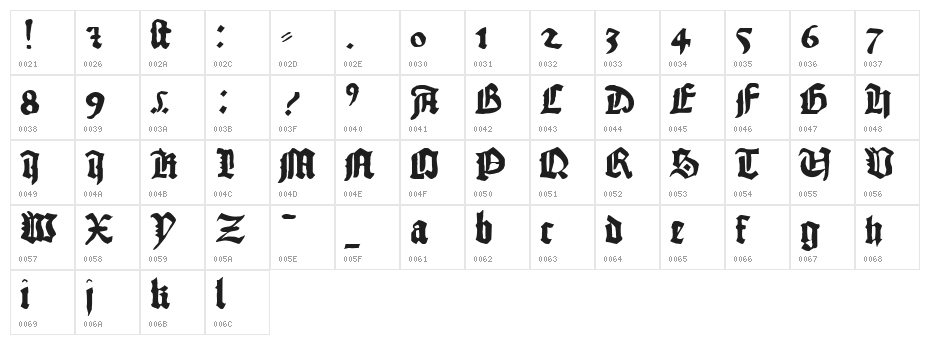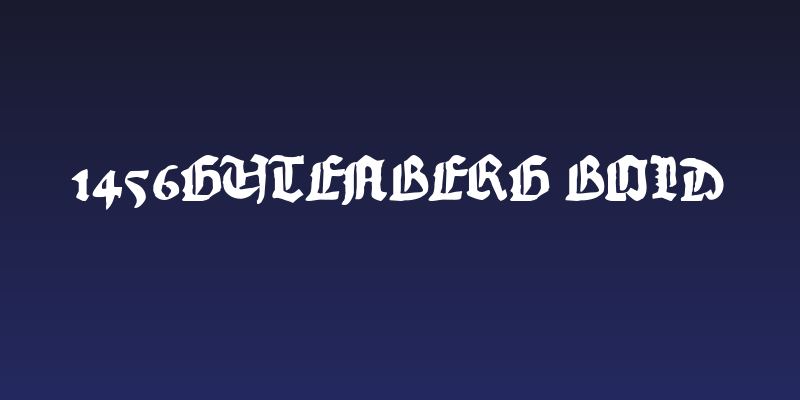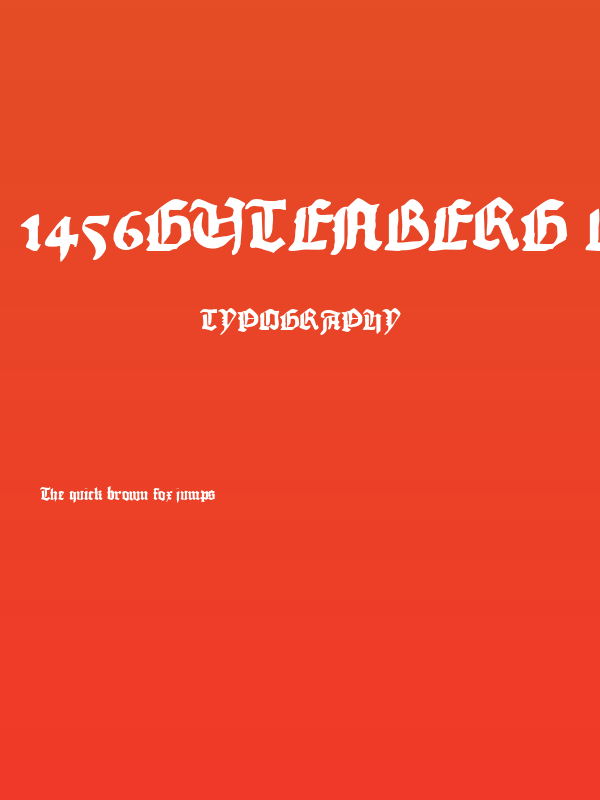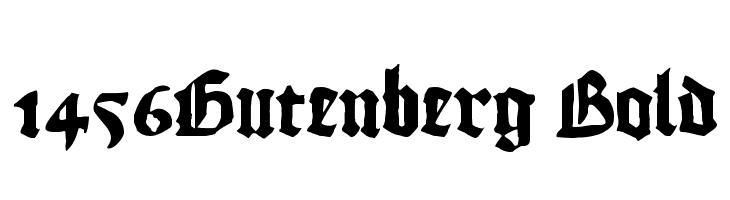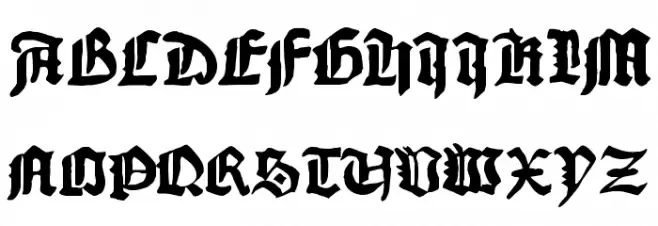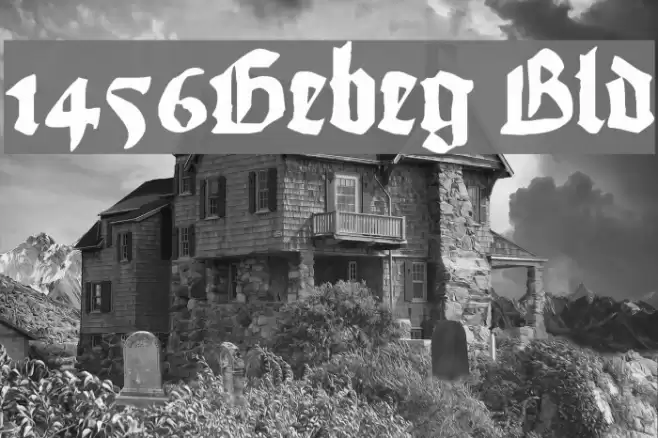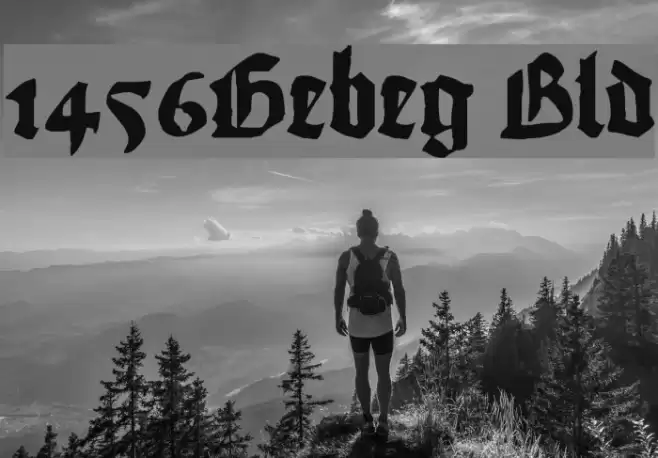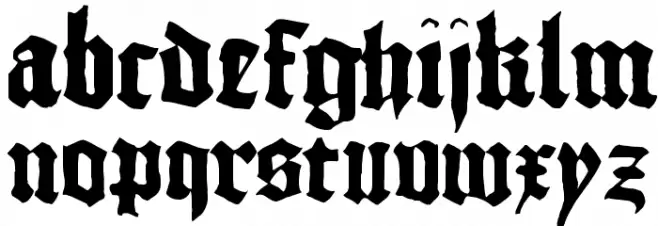
1456Gutenberg Bold Font
| Projets proposés | Ideal for historical or medieval-themed projects, book covers, posters, and branding that requires a classic, Gothic touch. |